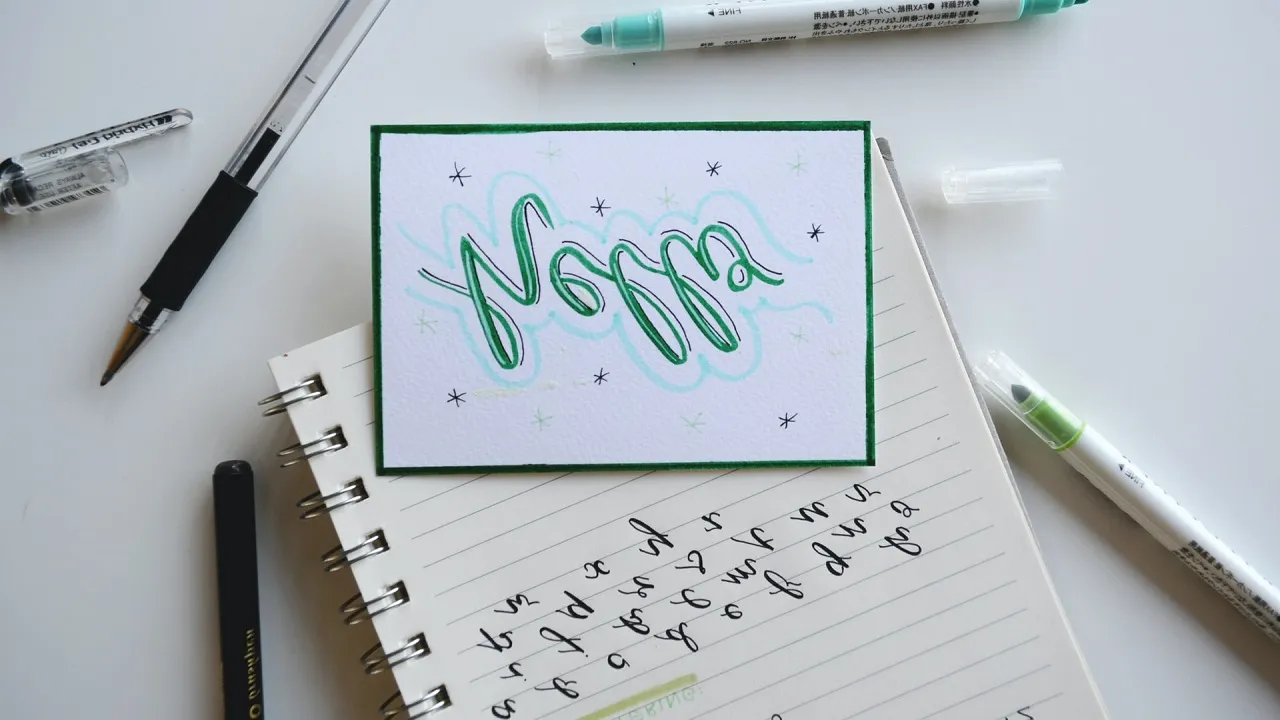
Daftar Font Tegak Bersambung
27 Font Tegak Bersambung Keren dan Aesthetic (+Download)
Bagi kamu yang ingin membuat desain dekoratif, kamu bisa mencoba memakai font tegak bersambung. Karena kebanyakan font tegak bersambung memiliki sisi keindahan dan keunikan tersendiri.
Alasannya mungkin karena font jenis tersebut mengandung beberapa gaya, misalnya seperti handwriting, kaligrafi dan lainnya.
Rekomendasi Font Tegak Bersambung
1. Stylish Calligraphy Font
Font Stylish Calligraphy
Pertama ada Stylish Calligraphy. Sesuai dengan namanya yang berarti font ini mengusung gaya kaligrafi modern.
Tulisan tegak bersambung di font ini juga didesain semenarik mungkin. Seperti adanya coretan diujung karakter dan penambahan karakter khusus yang bisa disambung.
2. Bulgatti Font
Font Bulgatti Script
Selanjutnya ada font yang memiliki gaya terkesan mahal, yaitu Bulgatti. Font ini mengambil gaya handwriting dengan konsep vintage.
Kalau kamu mendownload font ini, maka kamu bisa mendapatkan desain karakter huruf besar, kecil dan simbol khusus.
3. CADILLAC Font
Font Cardillac Hadwriting
Caddilac font mengusung gaya tegak bersambung yang terkesan cukup tinggi. Alasannya mungkin karena font Caddilac ini juga memakai format italic layaknya penulisan tegak bersambung.
Dari spesifikasi dan bentuk font tersebut, Caddilac sering dipakai untuk pembuatan tatto dan desain sablon baju.
4. Qaskin Font
Font Qaskin Handwriting
Selain Cadillac, font Qaskin juga sering dipakai untuk pembuatan tatto. Font ini mengambil desain handwriting modern, sehingga sangat layak dipilih kalau kamu tipe orang kekinian.
Menariknya, Qaskin font ini menyediakan 2 jenis font, yaitu Regular Style dan Qaskin White yang mengusung desain tanpa fill.
5. Lovely Coffee Font
Font Lovely Coffee
Kembali lagi ke gaya kaligrafi, maka kamu bisa pakai Lovely Coffee font. Font dengan desain tipis ini sangat direkomendasikan dipilih untuk kebutuhan pembuatan projek dekoratif.
Font ini menyediakan 248 karakter yang bisa kamu pakai setelah mengunduhnya. Karakter ini terdiri dari huruf besar, kecil, angka dan simbol khusus.
6. Angeles Font
Font Angeles Calligraphy
Angeles merupakan salah satu jenis font tegak bersambung yang dibuat khusus untuk pembuatan tatto.
Mengusung desain menarik, dimana ada goresan di setiap karakter membuat font ini terlihat cantik. Ditambah adanya efek shadow di beberapa karakter di font Angeles.
7. Better Grade Font
Font Better Grade
Kalau kamu mencari font tegak bersambung dengan gaya signature, Better Grade ini sangat direkomendasikan.
Alasannya karena font desain ini memiliki desain modern. Sehingga projek yang kamu kerjakan akan terlihat elegan.
8. Shalma Font
Font Shalma Calligraphy
Untuk font tegak bersambung dengan format bold, Shalma ini cukup kami rekomendasikan.
Selain mengusung format bold, Shalma juga mengambil gaya modern kaligrafi. Tapi kalau dari bentuk, font ini lebih disarankan dipakai untuk membuat desain yang feminim.
9. Junitta Font
Font Junitta Calligraphy
Ada yang sedikit mirip font Shalma, yaitu Junitta. Bedanya dengan Shalma, font Junitta ini lebih terlihat soft karena ketebalannya lebih tipis.
Namun keduanya sama-sama mengusung desain modern kaligrafi feminim. Sehingga membuat desain di font ini terlihat cantik.
10. Houstelly Signature Font
Font Housltely Signature
Houstelly Signature adalah salah satu font yang memakai desain signature atau berbentuk tanda tangan.
Font buatan Halymunstudio asal Indonesia ini sangat direkomendasikan kalau kamu ingin membuat desain dengan huruf tegak bersambung yang kental.
11. Tomatoes Font
Font Tomatoes Cursive
Lalu ada Tomatoes font dengan desain cursive-nya. Font ini terlihat sangat dekoratif karena di setiap karakter terdapat coretan yang cantik.
Font yang dirilis sejak tahun 2019 ini memiliki 293 karakter. Terdiri dari huruf besar, kecil, karakter khusus dan simbol-simbol spacing.
12. Candy Cane Font
Font Candy Cane
Candy Cane adalah salah satu font yang sering dipakai untuk pembuatan desain sablon baju. Font yang mengusung konsep handwriting ini sangat layak dipilih karena memiliki desain unik.
Desain unik itu terletak di setiap karakter, dimana ada goresan sehingga fill atau warnanya tidak merata.
13. Cassandra Font
Terutama kalau dipadukan dengan desain bernuansa cerah.